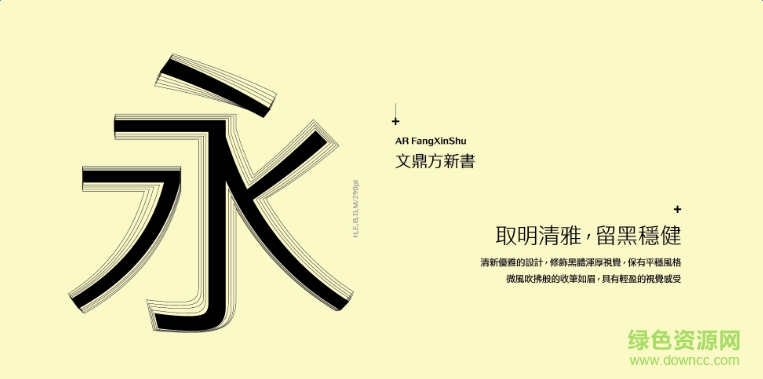
文鼎方新書(shū)是問(wèn)鼎科技新推出的一款中文簡(jiǎn)體字體,這款字體筆畫(huà)簡(jiǎn)練,字型優(yōu)雅,粗細(xì)搭配到位,看上去舒適清爽,識(shí)別性強(qiáng),應(yīng)用范圍廣泛!
方新書(shū)秉持穩(wěn)重、簡(jiǎn)單的設(shè)計(jì)風(fēng)格,以高規(guī)格審視標(biāo)題用字之識(shí)別性、內(nèi)文用字易讀性,期望帶給使用者最佳的使用體驗(yàn),刻意縮窄的字身讓方新書(shū)再多了幾分詩(shī)意。
文鼎方新書(shū)的造型設(shè)計(jì),修飾了黑體的渾厚視覺(jué)感受,融入輕柔優(yōu)雅的設(shè)計(jì),但仍保有黑體字型的簡(jiǎn)約平穩(wěn)風(fēng)格;字型特征在于如清風(fēng)吹過(guò)般的收筆如眉,讓方新書(shū)有別于黑體呈現(xiàn)出一種輕盈視覺(jué)感受。
文鼎方新書(shū)是在黑體的基礎(chǔ)上設(shè)計(jì)出的一款新字體,字體結(jié)構(gòu)平穩(wěn),線條流暢,便于閱讀,喜歡這款字體的朋友就來(lái)綠色資源網(wǎng)下載吧!